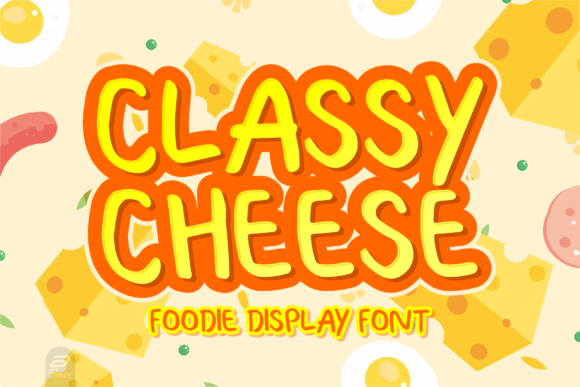
[Creativefabrica] Classy Cheese Font (2021)
Classy Cheese - это классный, спокойный и адаптируемый шрифт.
Этот адаптируемый шрифт будет отлично смотреться на различных дизайнерских идеях.
Он добавит веселый и дружелюбный штрих к каждому вашему проекту!